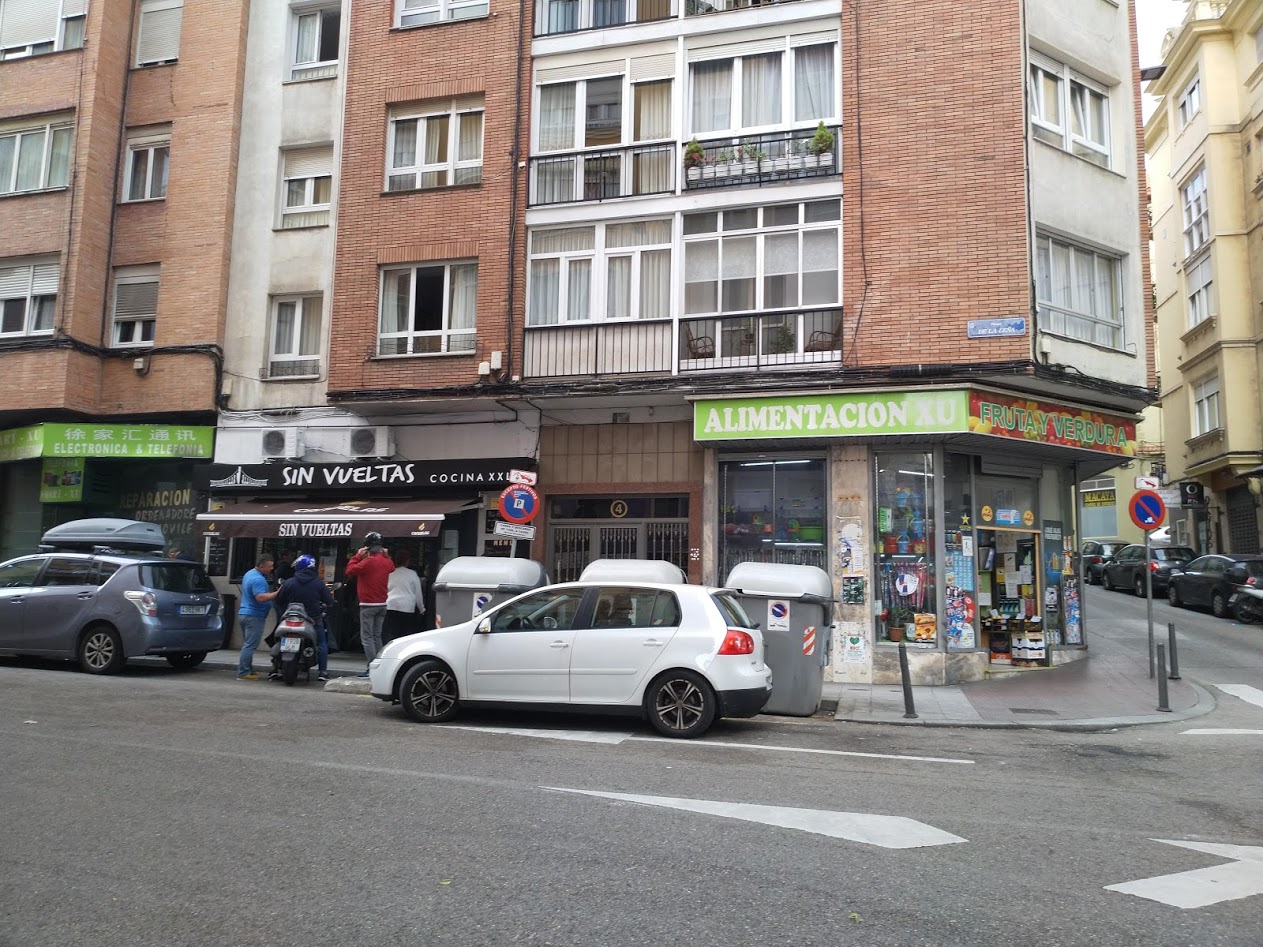
Cuando un rótulo se convierte en un icono del barrio
Cuando hablamos de que los rótulos son patrimonio, no es a veces sólo porque se realizase de manera artesanal en vidrio, madera, cerámica o metal, si no también porque se hace parte intrínseca de un barrio o una calle. Se convierte en un icono visual de la memoria colectiva de la comunidad de la zona y del imaginario popular, que en muchos casos toma entidad propia y modifican el reconocimiento del territorio convirtiéndose en referente de la zona.
Para ilustrar esta entrada, traigo el ejemplo de La Mejillonera. El negocio original se funda en Valladolid, en los años setenta de la mano de Jesús González Abadía. Su modelo de Patatas en Salsa y Mejillones, rápidamente se expande a otras catorce ciudades, entre ellas Santander en 1973, en la Plaza de la Leña. Aquí se convirtió como un local de referencia, donde en los mejores momentos se llegaban a vender 50 kg de mejillones a la semana.
Al frente de este éxito estuvo Alberto del Valle, que llegó de Palencia a mediados de los 70 para cubrir una baja y se convirtió en el encargado de cerrar uno de los locales más míticos de Santander el 31 de mayo de 2014. En 2015 reabrió el local convertido en un restaurante de comida turca, pero mantuvo el rótulo intacto. No le fue bien y cerró. Tras un par de años más cerrado, llega la pandemia. En cuanto se abrió la fase 3 de la desescalada, me avisaron de inicio de obras en el local y de que se está rompiendo el rótulo. Poco se podía hacer ya, más de 40 años en un barrio que acabarían como chatarra y en la basura.
Ahora al pasar por la zona queda rastro de ese espectacular rótulo que sobrevivió a todos los cambios de negocio en el barrio y se convirtió por motivos propios en un icono colectivo y visual de la zona. Ahora sólo queda el recuerdo gráfico y en la memoria de lo que antaño fue.
Es por ello que somos nosotros, los vecinos de la calle, quienes debemos velar por nuestro patrimonio cotidiano y que, ante el riesgo de desaparecer, podamos preservarlo.
PD: Deseando la mejor de las suerte al nuevo negocio, esta entrada sólo pretende hacer reflexionar del valor, a veces inmaterial, que un rótulo tiene para una ciudad.